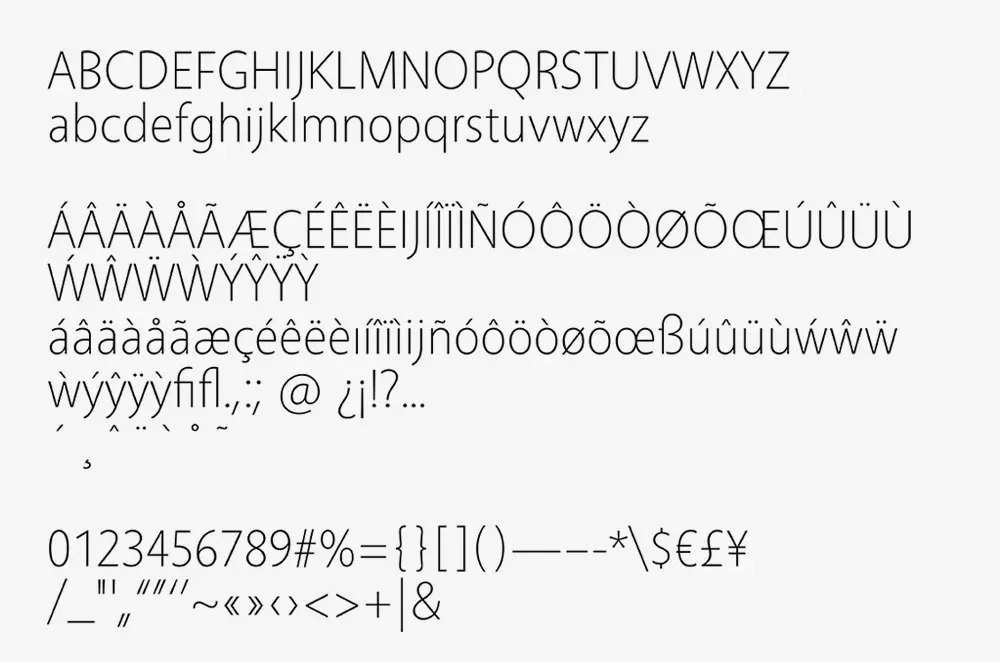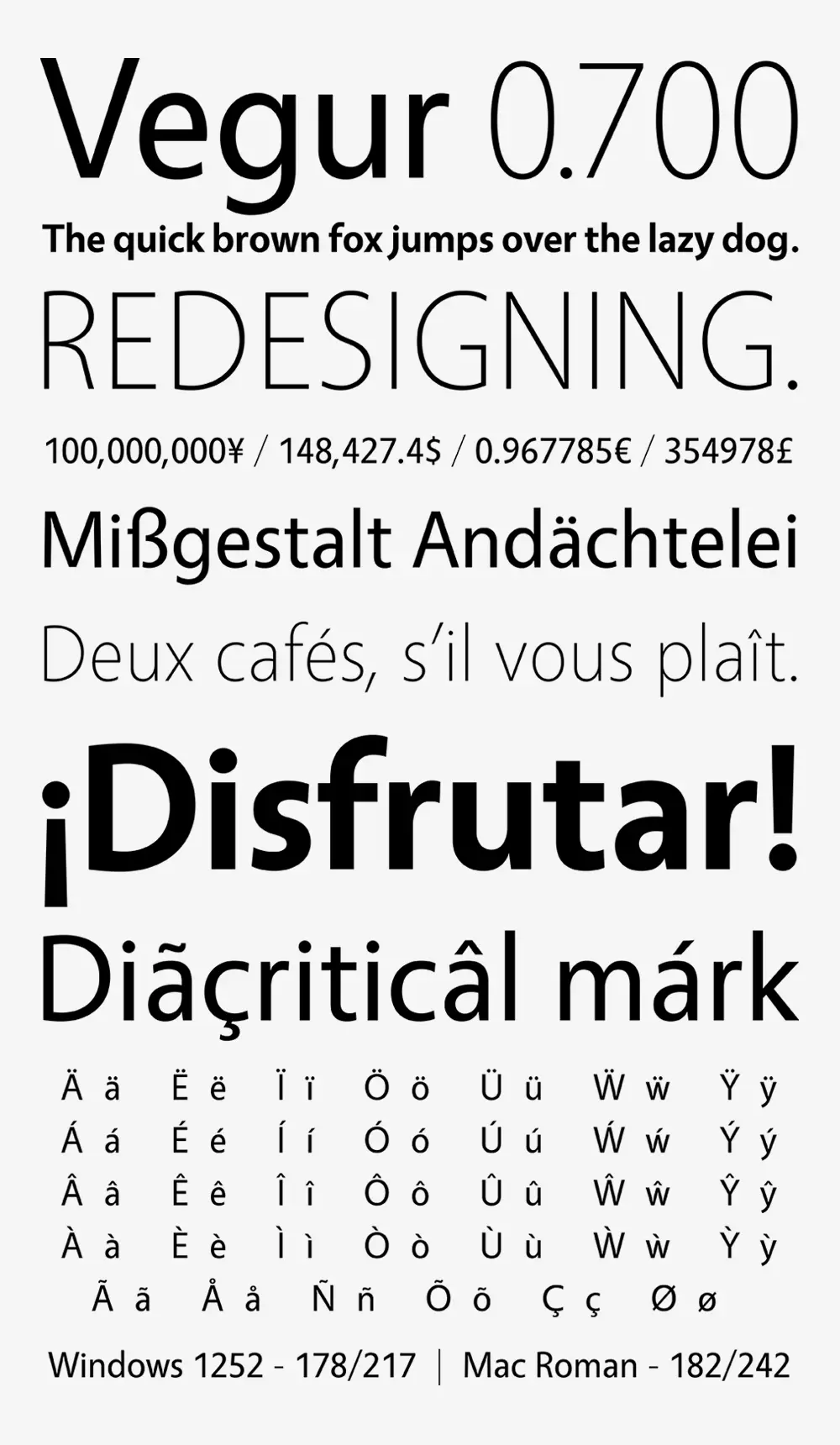
Vegur介紹
Vegur 是一種人文主義無襯線字體,專為點冒號標識而開發。藉著更新0.700版本的機會,我們重新審視了設計,修復了拉伸的部分,以創造出更銳利的印象。它還被調整為比之前的版本更長,整體看起來更乾淨。特別是,我認為已經推遲的粗體字號的印象通過這次更新有了很大的改變。
此外,我們還添加了大量字符,例如變音符號(添加到字母表中的符號)、連字(例如法語中的 Æ 和 Œ 以及德語中的 ß)。此外,我們還添加了英鎊(英鎊)和歐元(歐元)等代表性貨幣符號,以及歐洲國家的標點符號。儘管並非所有字符和符號均可用,但我們計劃在未來的更新中添加更多字符和符號。
作為高級版本,我們發佈了Route 159,它經過重新設計,字形數量顯著增加。
Vegurはdot colonのロゴタイプ用に開発されたヒューマニストサンセリフフォントです。0.700バージョンへのアップデートを機にデザインを一から見直し、間延びしていた部分を整えシャープな印象に仕上げました。 また、以前のバージョンよりも長體気味に調整し、全體としてすっきりした印象になるようにしています。 特に間延びしていたBoldウェイトも今回のアップデートで大きく印象が変わったと思います。
そのほか、ダイアクリティカルマーク(アルファベットに付される記號)やフランス語のÆやŒといった合字、ドイツ語のßなどの文字を大幅に追加しました。 さらに、£(スターリング・ポンド)・€(ユーロ)といった代表的な通貨記號や歐州圏の約物記號も追加しました。 まだすべての文字・記號が揃っている訳ではありませんが、今後のアップデートで順次追加していく予定です。
発展型として、デザインの刷新と収録グリフ數を大幅に増やしたRoute 159を公開しています。